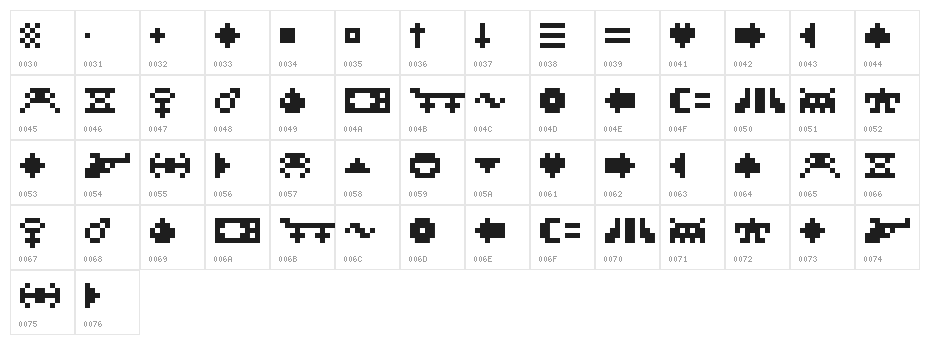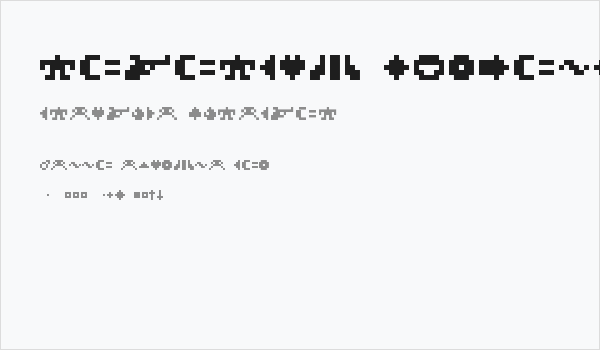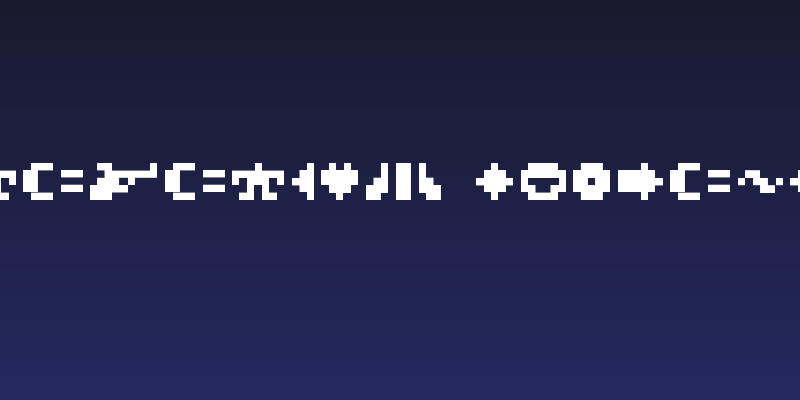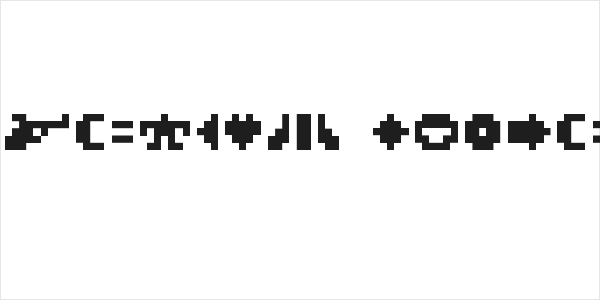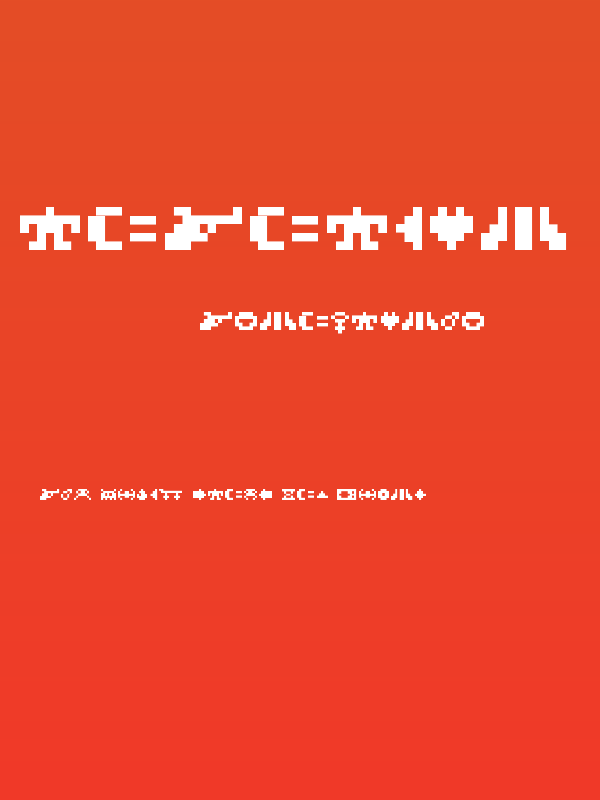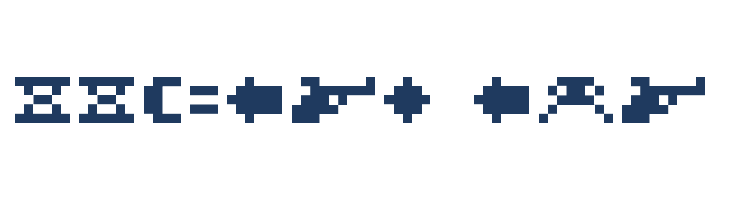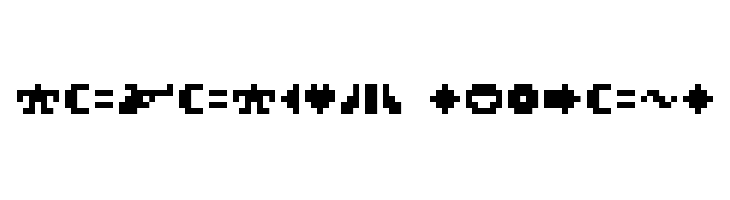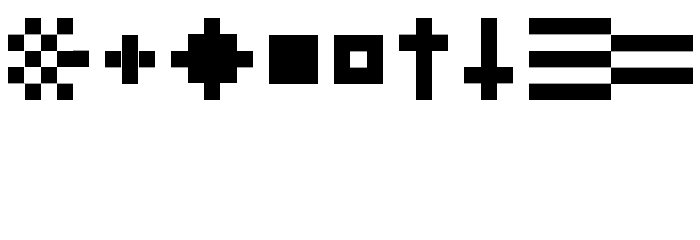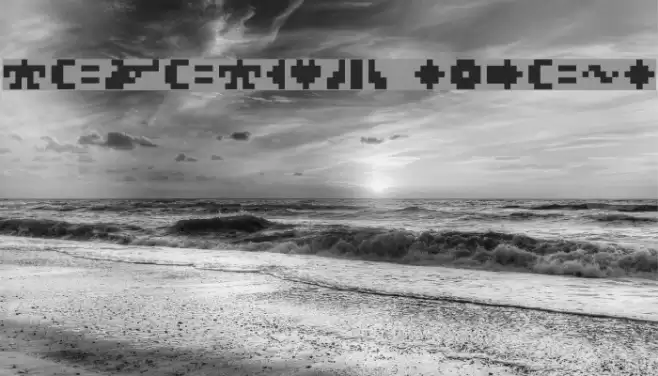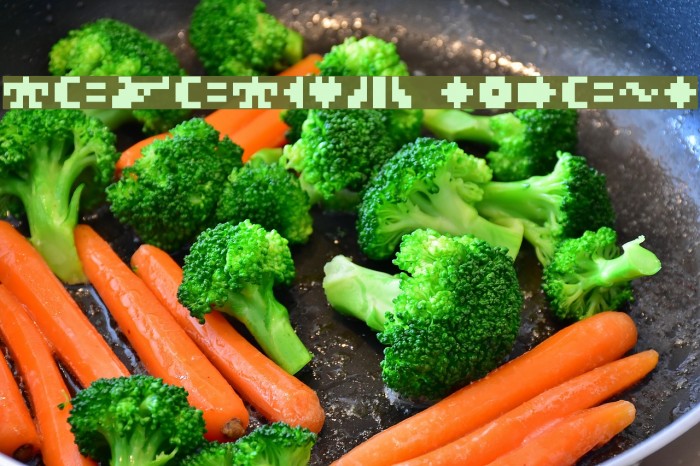
ROTORcap Symbols Font
| النمط العام | Retro, Digital, Geometric |
| حالة الاستخدام | Logos, Digital art, Video game design |
| مشاريع مقترحة | Ideal for video game design, digital art projects, retro-themed graphics, and tech-related branding. |